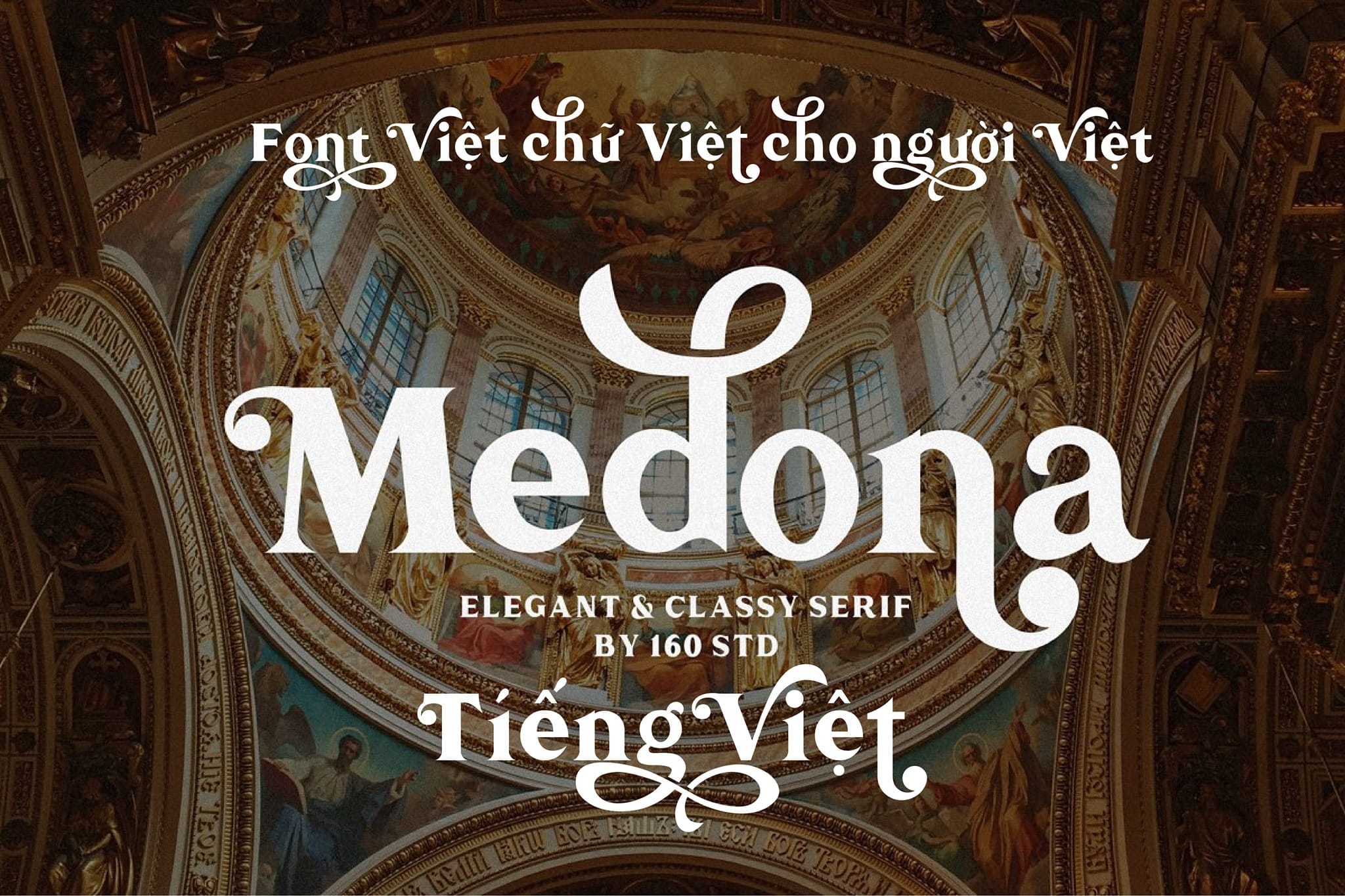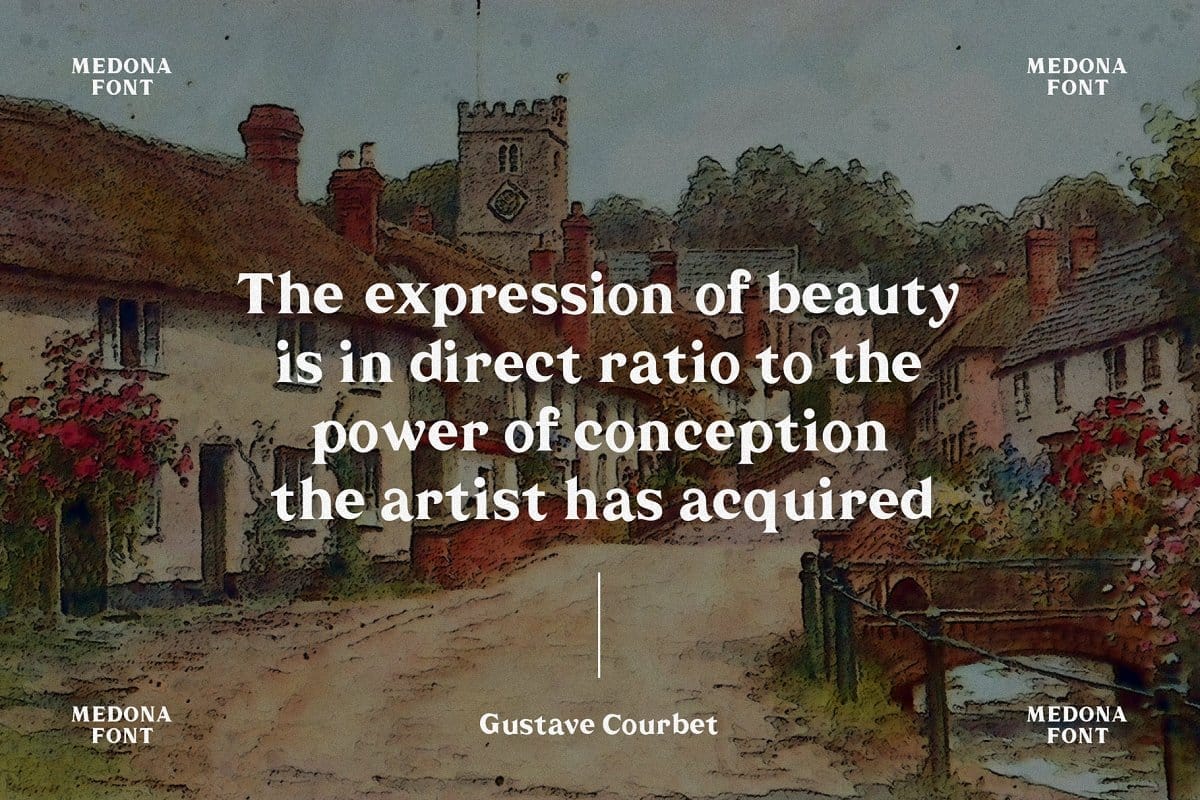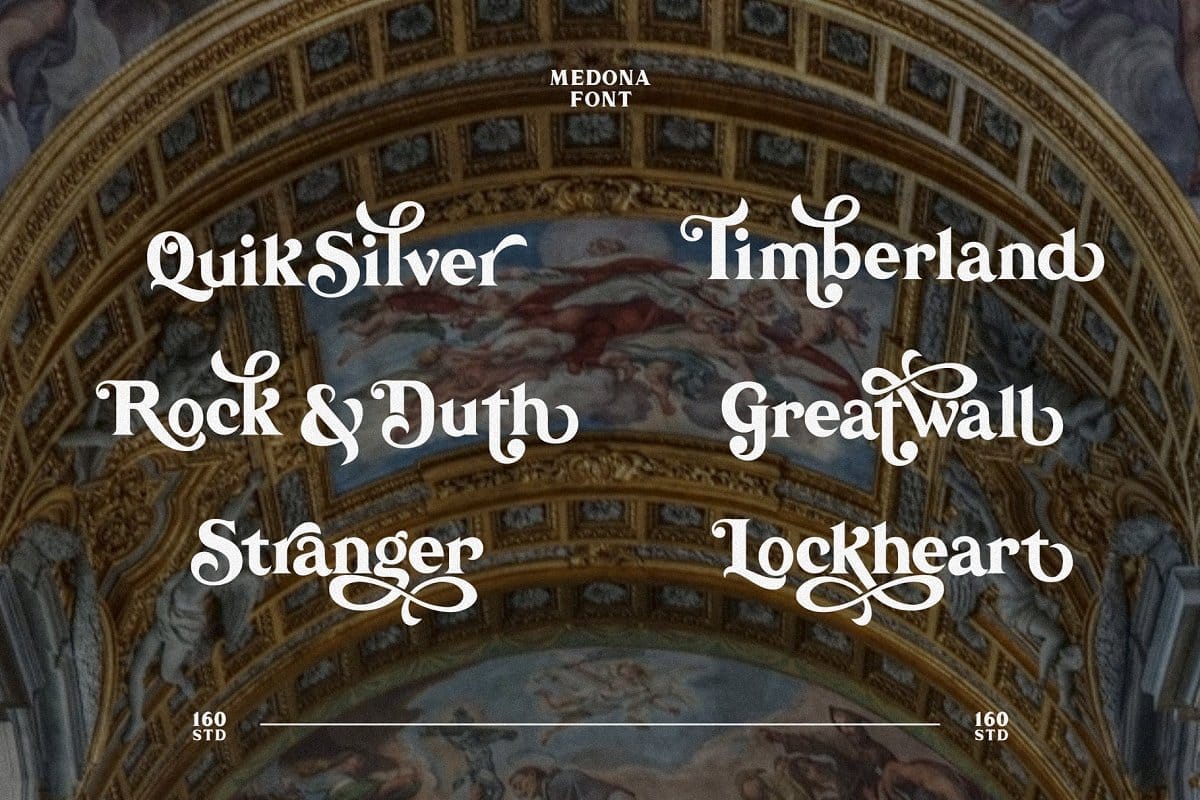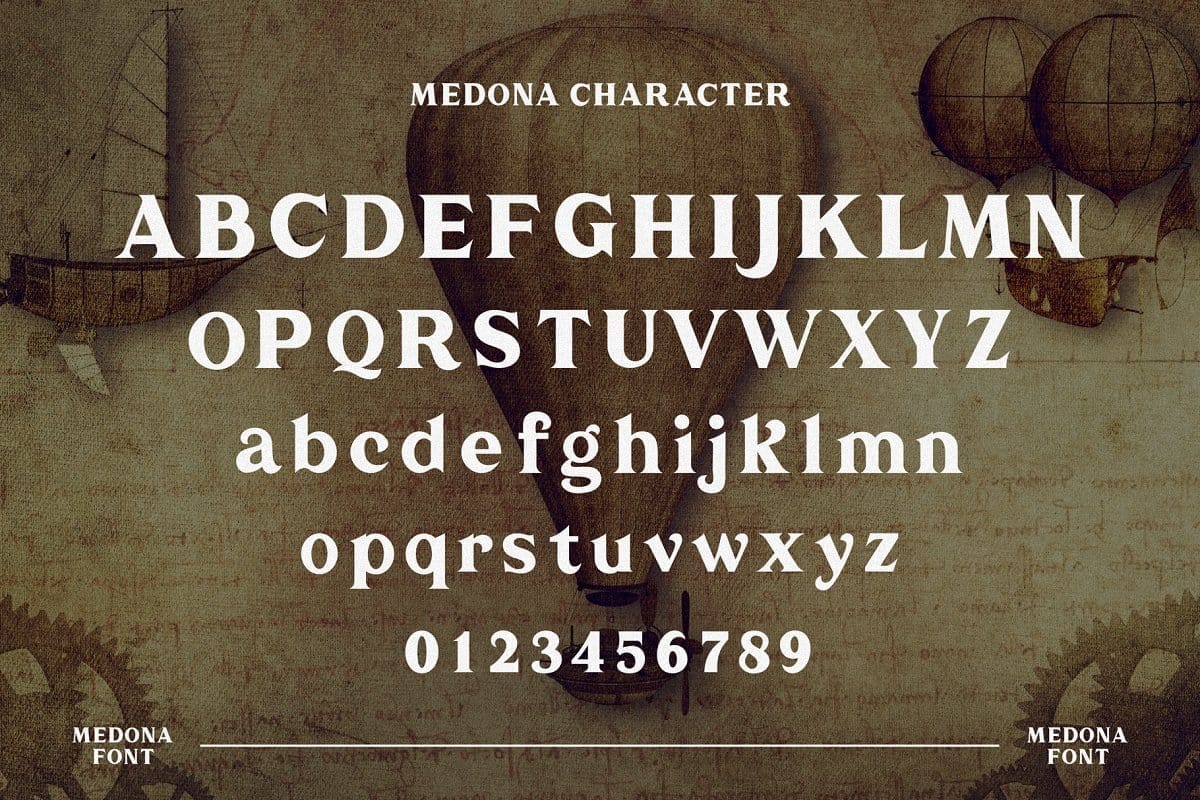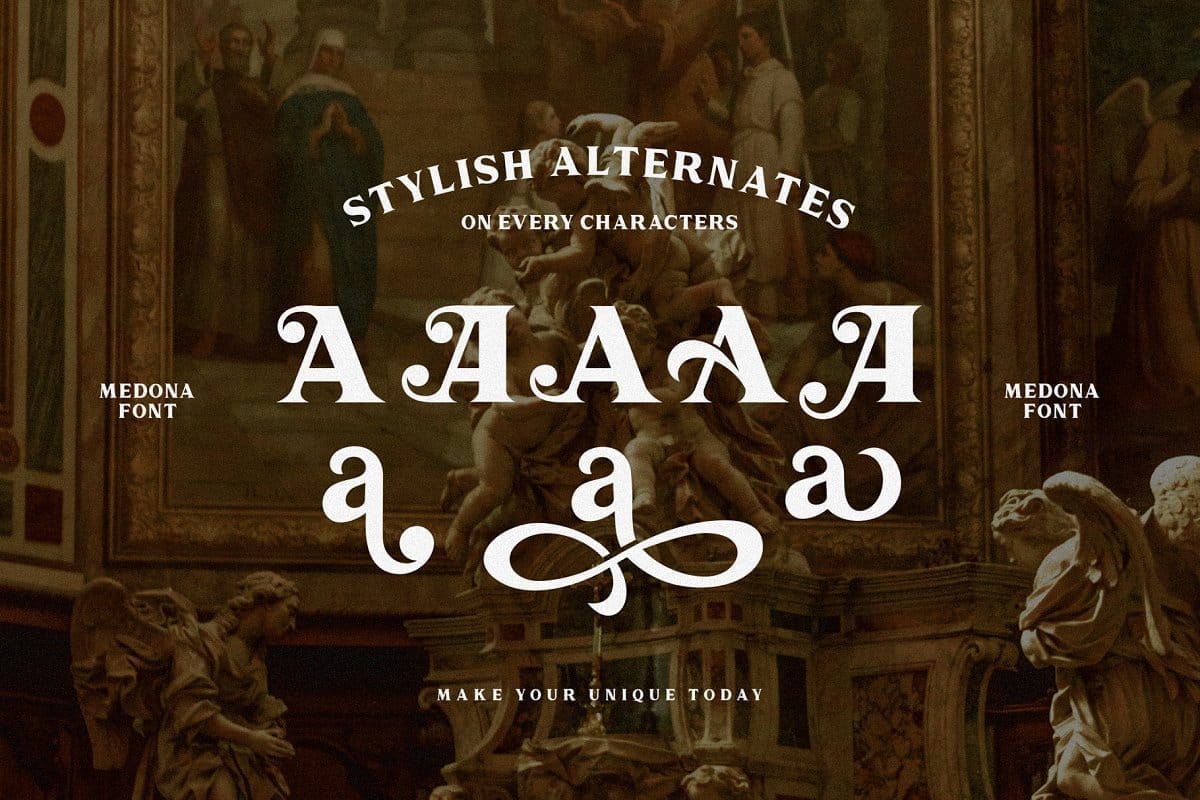
Font Medona Việt Hóa – Font nhiều glyph đẹp
Giới thiệu về font Medona Việt Hóa Đây là dạng font Serif khá đẹp với hơn 200 thay thế minh họa bằng tay, cho một cảm giác cổ điển độc đáo, nhưng hiện đại.
Mỗi chữ cái có một số đồ trang trí hoạt động đẹp mắt để tăng cường cho phông chữ Medona, các chi tiết thông thường. Phông chữ này có đủ ký tự cho logo và thương hiệu, cũng như các tiêu đề, trang trí và nhiều hơn nữa.